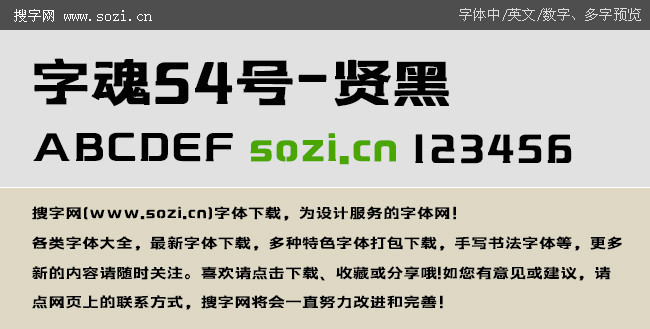
字魂54號-賢黑
搜字網(wǎng)提供一款字魂54號-賢黑中文字體下載,該字體是一款黑體創(chuàng)意字體,該字體包含6763個中文、字母、 符號和數(shù)字,具有有力、穩(wěn)重、大氣 的風(fēng)格,可以滿足您設(shè)計上的各種需求,該字體主要用于屏幕、印刷品、屏顯、印章、企業(yè)慶典、社交、活動 等場景。